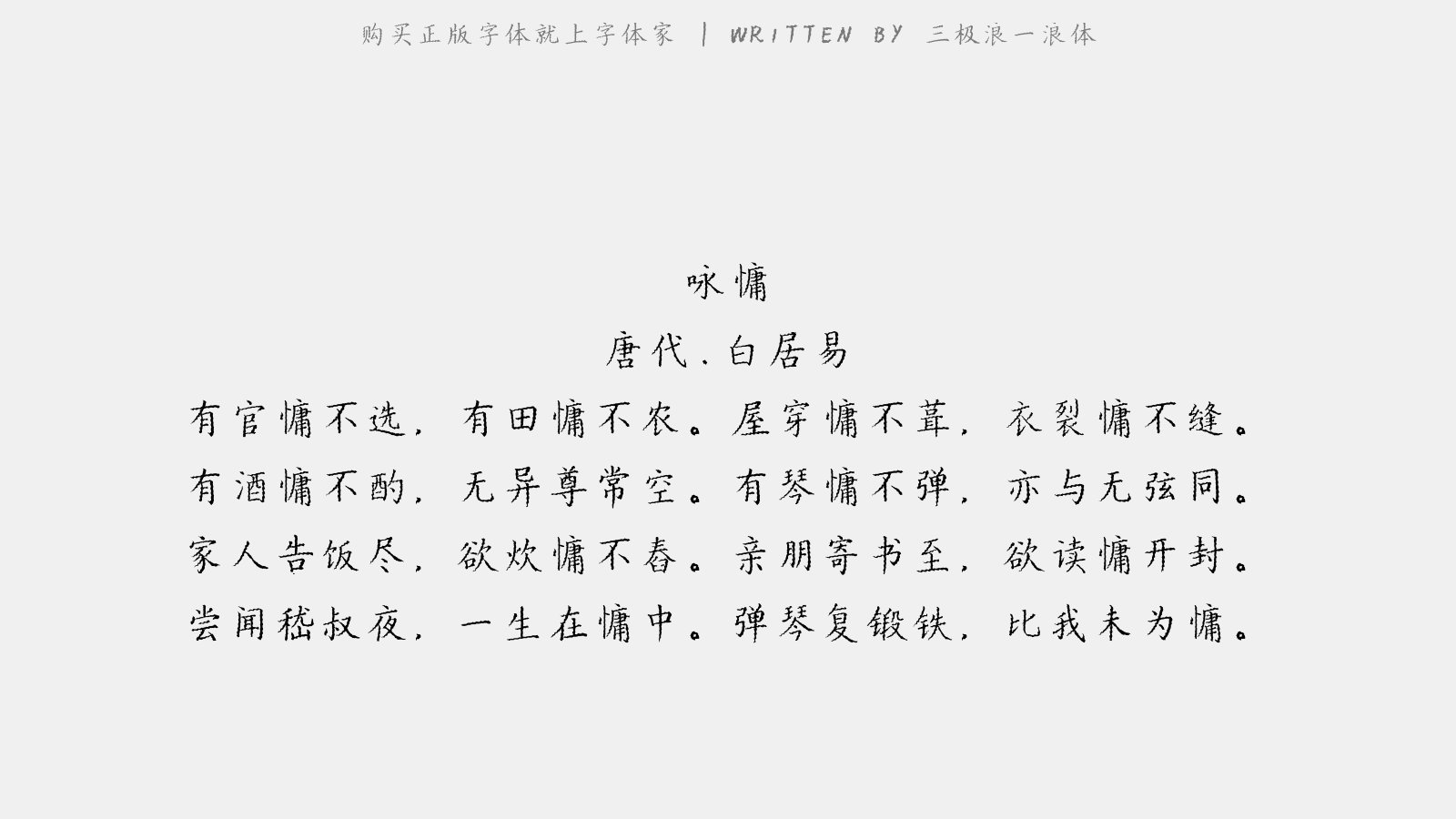
三极浪一浪体
字体作者:三极字库
字体名称:三极浪一浪体
字体家族:三极系列
书体类型:手写体/拼音
字体公司:三极字库
三极浪一浪体
三极浪一浪体是一款非常不错的艺术字体,由三极字库出品,工整简洁,具有强烈的视觉冲击力,适应于报纸和杂志和书籍中常用字体, 海报、个性促进品牌标志设计、字体设计、等环境使用,欢迎喜欢的朋友前来字体家下载使用。